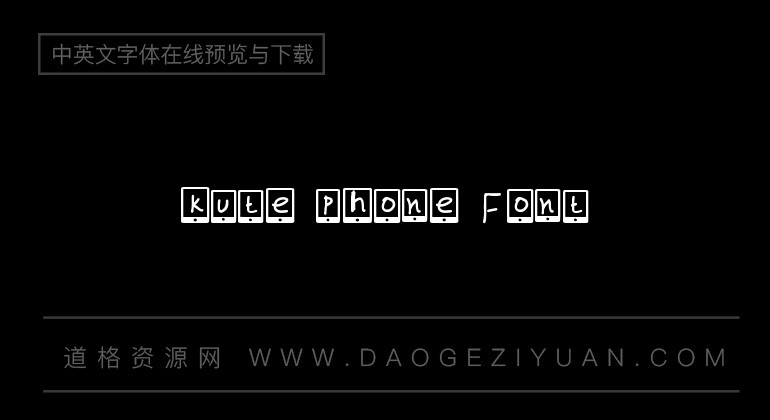
kute phone Font
Kute phone Font是一种流行的手写风格字体,目前在移动设备上非常受欢迎。它的设计风格简约、清新,字母线条流畅、圆润,符合现代人对简单自然的审美需求。 该字体适用于各种移动设备,如手机、平板电脑等,是一种非常适合阅读和浏览的字体。它可以帮助用户更好地阅读和理解文本内容,并且给人以轻松愉快的阅读体验。 Kute phone Font字体可以用于许多不同的场景,比如手机应用程序、网站、广告、海报等。它的使用可以为你的设计增加一份亲切、温馨和自然的氛围,为用户提供更好的用户体验。
kute phone Font是一款非常不错的手写艺术字体,具有很好的视觉感,适合于文化类的宣传设计、商业类品牌的广告和产品包装设计以及个性化文字排版等较多场景。